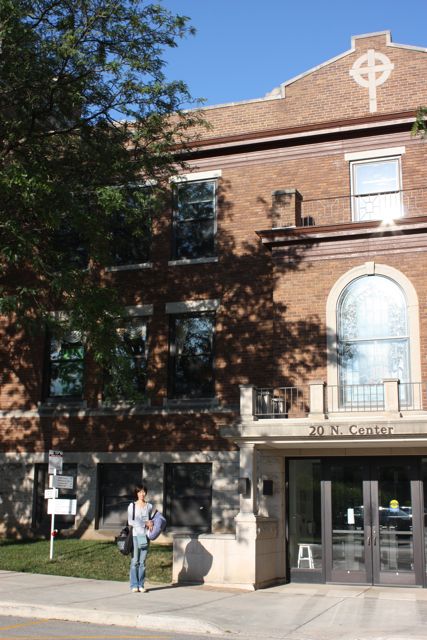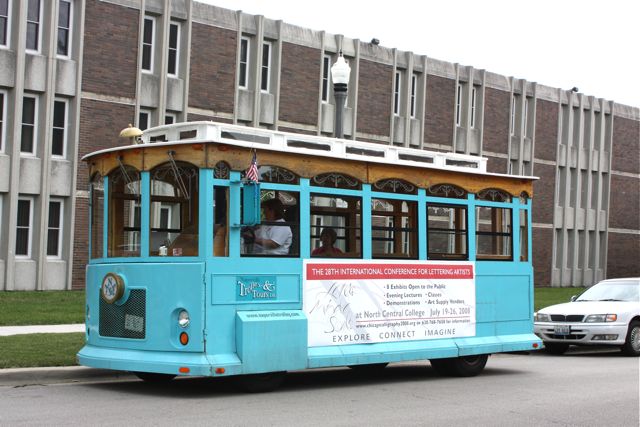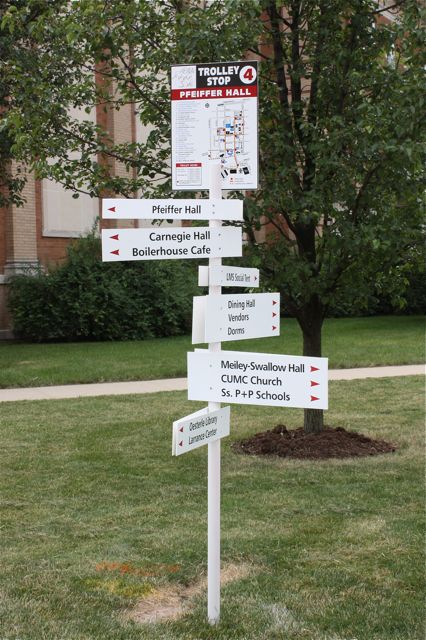
モジトルカードエクスチェンジ7月の誕生日カード
7月も最終日となりました。セミがいっせいに鳴きだし、暑い毎日、雷多い、豊作?!大きなスイカがごろごろ売っているこの夏!
送られた誕生日カードをご紹介いたします
KIさんへのお誕生日カードです。作者はRIさん。
封筒は半透明の紙でできています。中がほんのり透けて見えて期待がふくらみますよね。(みなさん、こういう紙の使い方が本当にお上手なので、いつも参考になります)
中身の色は赤なのですが、こうするとやわらかピンクに見えます。
その色にあった切手が貼ってあって、かわいい!
さて、次に赤い封筒が…隅に模様がついています。あ、エンボスされているんですね。
パーチメントクラフトの技法なのでしょうか。
見えますか〜?For Youの文字のあとにもちっちゃ〜くお花模様が入っています。
紙はクロマティコかしら、厚手の半透明紙です。
そしてそして、その中に入っているのが、こんな華やかなカード。
円の中の文字の色を変えてあるから、きれいな円形になっているし、Happy Birthdayの文字が強調されて、いいですね。
四隅のカットワークは、手でカットされているのでしょうか?こんな細かいレース模様が…すごい…
小さなところにもこだわりを持って作られた、RIさんの気持ちが伝わってくるカードです。
こちらは、HNさんへのカードです。作者は、KIさんです。
和綴じの5×4cmくらい(測り忘れてしまい、ごめんなさいm( _ _ )m )のミニサイズの本です。
ページを開いていくと、Happy Birthday Best wishes on your special day!
となります。そして、小さな花と落款も!!!文字は、ウォールナットインクでしょうか?!HKさんもきっとページをめくりながら微笑んだのではないでしょうか〜
小さいのに、とても丁寧な仕立てで作られていているんですよね〜。
カードといっても、このような形体あって、とっても新鮮!!!納得!!!
他の毎月のカードは、中身が見れないので残念ですが、大きさ様々、重いものもあり、いったいいったいどんなのだろうと、毎回とても見たい気持ちでいっぱいになります!
シカゴから
シカゴで開催された第28回インターナショナル・カリグラフィー・カンファレンス「Letters Mingle Souls」に参加してきました。
久しぶりのアメリカでのカンファレンス参加です。2001年にボストンで開催されたのに参加したのが最後で(そのすぐ後に9.11同時多発テロがあったこともあり)しばらくアメリカへは行っていませんでした。
今回は行くまでの日常が忙しく、詳細は飛行機の中で確認したりしたこともあり、実感がないまま行き、アメリカには住んでいたこともあり、外国へ来た!という感覚があまりないまま、結局帰国した感じです。
シカゴから車で45分くらいのところにあるNapervilleというところにある、North Central Collegeが会場です。非常に広い構内なので、こういったトロリーバスが走っています。泊まる宿舎、食事をするダイニング、クラスのある教室、それぞれが離れているので、時間に間に合う様にするにはいつも一生懸命歩きます。そして時々これにも乗りました。遊園地みたいで楽しいです。
そんな構内で見つけたこんな木。おもしろ〜い
教室のあった建物は、実は教会です。
その前でパチリ。
左手に抱えているのは、枕です。
教室の机が高く、椅子は低く、長身で机の高さで不便を感じた事がない私ですが、今回ばかりは、クッションが必要でした。お尻の下に敷いて書いていたのです。という訳で、こうして毎日枕を風呂敷に包んで持ち歩いていました。
Letter Arts Exhibition Summer 2008
昨日から羽ペン工房でLetter Arts Exhinition Summer 2008が開催されています。
2008年夏〜2009年春の一年間で4回、J-LAF主催で作品展を開催します。第1回目となる今回は、J-LAFスタッフによる作品を展示しています。(今後この作品展はどなたでも参加出来ます。第2回目は9月末〜10月中旬を予定しています)作品は示し合わせた訳ではないのに、色がなんとなく揃っていて、とても良い空間です。文字が主体の作品、コラージュ作品、パネル張り、板にそのまま書いたもの、和紙を使ったもの、それぞれ素敵な作品ばかりです。
この作品展を主催しているジャパン・レターアーツ・フォーラム(J-LAF)は、カリグラフィーを軸とした日本におけるレターアーツ(文字芸術)の芸術性向上、レターアーツを介した海外との文化交流を目指し、その支援と交流を押し進めていく非営利団体として2008年2月に設立されました。
現在日本にあるカリグラフィーを含むレターアーツが、芸術の一翼を担うものとして広く認知されていくことを目的とし、アート活動の支援やアーティスト同士の交流を深めていきます。
J-LAFや羽根ペン工房のロゴもパンフも素敵ですよ〜!
St.Gallen では…。
St. Gallenといえば、カリ人の間では有名ですね・・・。
スイスのチューリッヒから電車で2時間ぐらい、
小さな駅を降りると、St. Gallenです。
とても威厳のある教会があり、写本や図書館が
素晴らしいです。
図書館はバロックで、豪華なんですけど、
なぜだか奥の方にはミイラさまが横たわっておいでです。
運が良ければ、修道士さんたちの歌の練習が
聴こえてきたりして…中世の時間に入り込んでしまい
そうなときがあります。
S
St. GallenのHPを見ると今面白い展示をしているみたいです。
Geheimnisse auf Pergament 羊皮紙写本の謎・・・とでもいうのでしょうか・・・。
文字とは不思議なもので、謎はわからず、不可思議な記号のように思える・・・と
いうような説明で始まっいて、画像が本当にミステリアスなんですねぇ。
お時間がありましら、どうぞあなたもその謎の世界に浸りませんか?
・・・ええ、まぁ、ネットでね!フフフ。
紙好きなあなたへ
紙好きにはたまらない本が出ています。
たくさんの作家さんがご自分の作品を
紹介・・・。
どれもこれも素敵な作品ばかりです。
中身に使われている紙もさまざま…。
ページとページの間に遊び心の紙が
存在感を出しています。
これは何かな?と思いながらページをめくるのも
楽しいです。
私の好きな辻恵子さんhttp://www.tsujikeiko.com/、
今度製本を習おうと思っている都筑晶絵さんの
作品も載っていてうれしいです。
どうですか?
身の回りにはらりと落ちている紙も何かに変身〜するかもしれません!
「お宅のご主人が交通事故を起こし…」というものです。
「なんのことでしょうか?」と問い返すと、相手は慌てたような声でそそくさと電話を切ってしまいました。
その当時テレビなどでこの手の詐欺についてたくさん報道されていたので、本当の詐欺グループというよりもちょっとまねてみた、という程度だったのかもしれません。
うっかり者の私がなぜ、その日は冷静でいられたかというと…
実はその前日に友人が詐欺にあった話を聞いたばかりだったからです。
才色兼備、何をやっても優秀なその人でさえ、だまされてしまったのだから、私なんか簡単にだまされるのかも。
そう、思っていた矢先のできごとでした。
「用心している者にかぎってひっかかる」(プラウトゥスのことば)この言葉を読んだので、ふと、この電話のことを思い出したのであります。
これは「ギリシャ・ローマ名言集」(岩波文庫 赤123-1)にあった言葉です。
この本では名言の日本語訳のほかに原文も載っています。おもしろいのは、ほとんどの名言に解説がついていること。
それから各名言のテーマなどを見出し語としているところもユニークです。その見出しにつられて、読み進んでいきます。
もう一冊は「原文対照 古典のことば」(岩波文庫別冊10)
こちらはギリシャ・ローマに限らず、広く外国の古典から集められた言葉の数々です。
すべて岩波文庫の古典が出典で、書名が記されているので、もし興味を持てば読書へと進めるようになっています。
この本も原文が載っています。「論語」はもちろん中国語で。
これらの本はKさんやmkさんに教えてもらいました。ありがとうございます。
この頃は還付金詐欺?次々とだましのテクニックは向上していくようです。みなさまもご用心ください。
Letter Arts Exhinition Summer 2008
素敵なDMが出来上がりました!
Japan Letter Arts Forum(J-LAF)という新しい
カリ活動のグループが主催する記念の第一回目!
exhibition企画のSさん→グラフィック担当のIさん←タイトル制作カリ人Yさんの見事な連携で素晴らしいお仕事でした!
あと2冊作ればおしまいです。しかし…これ全部夏休みの宿題ですか…
こっちは本当のオードリーが
描いた絵!
オードリーは、
ユニセフの親善大使でした。
それで
ユニセフのために
こんなカードを作りました。
もうずいぶんと昔に
購入しました。
大事にしてます!
これこれ!
印刷ではありますが、
オードリーのサインですぅ。
ウフフ。
サコシュの時間だ・・・。今日の山岳はすごいぞ!
アルプスの山越えだもんね。クネゴとポポヴィッチの集団追走だぁ〜(独り言)